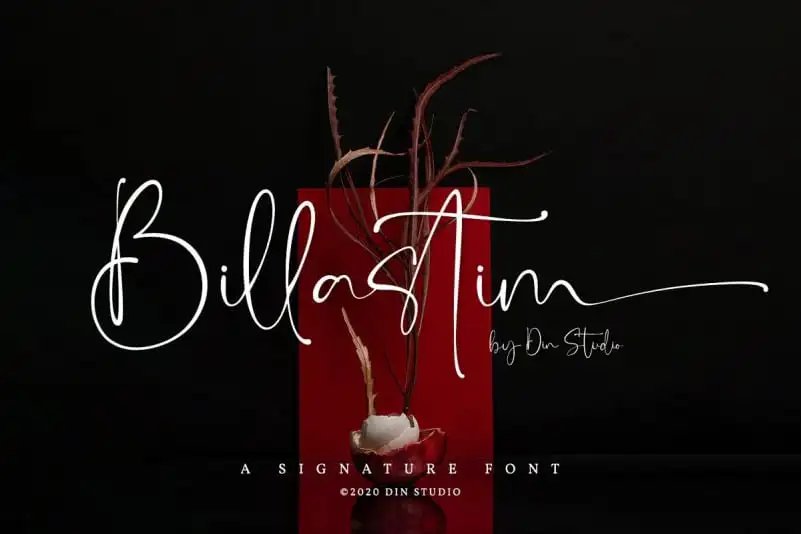
Billastim Script Font – Download Grátis
A fonte Billastim Script é uma escolha perfeita para designers que buscam diversidade nas apresentações de seus projetos digitais e impressos. Criada pela Din Studio, esta fonte tipográfica elegante e sofisticada enriquece a paleta de opções disponíveis aos profissionais do design gráfico. Ideal tanto para sua página web quanto para o seu branding em redes sociais, banners do Pinterest e até mesmo produtos impressos, Billastim Script oferece um toque único que pode transformar qualquer projeto no qual seja aplicada. Com uma elegância e sofisticação incomparáveis, esta fonte é perfeita para criar mensagens impactantes e capturá-los com estilo. Com a Din Studio como seu criador, você está garantido de encontrar qualidade e originalidade em cada letra e traço desta fonte.